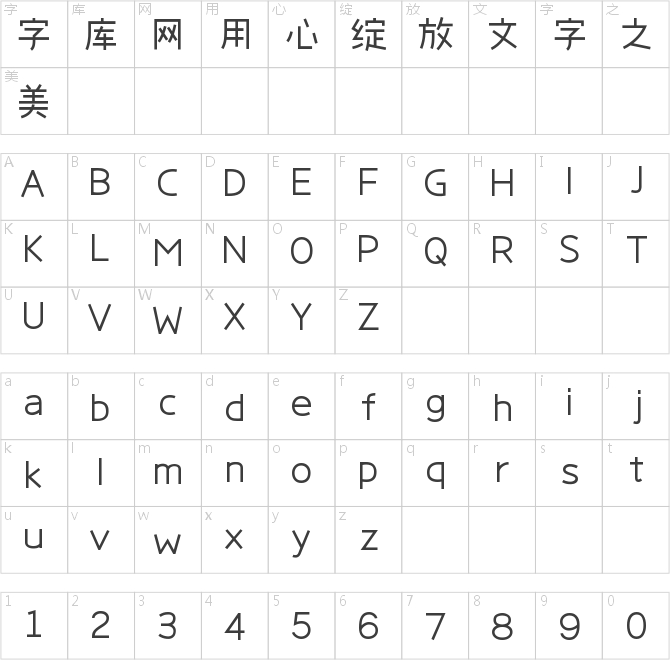
山海晴空日記,一款卡通風(fēng)非襯線字體,包含漢字簡(jiǎn)體6763個(gè)。字體童趣可愛,結(jié)構(gòu)多變靈動(dòng),字形活潑清新,造型生動(dòng)有趣,線條靈動(dòng)均勻,直線與弧線的完美結(jié)合,使字體具有靈活的適用性,天真俏皮又不失時(shí)尚感。